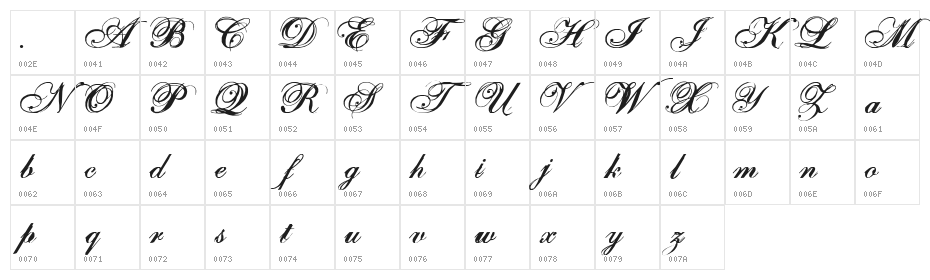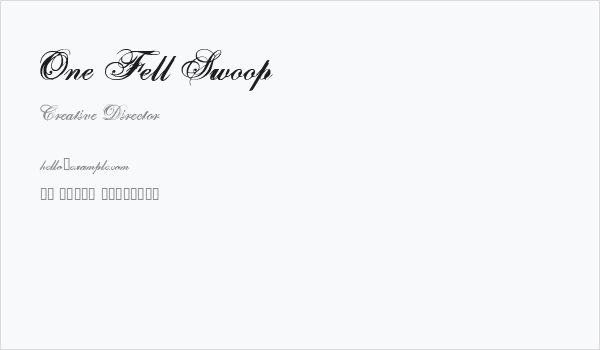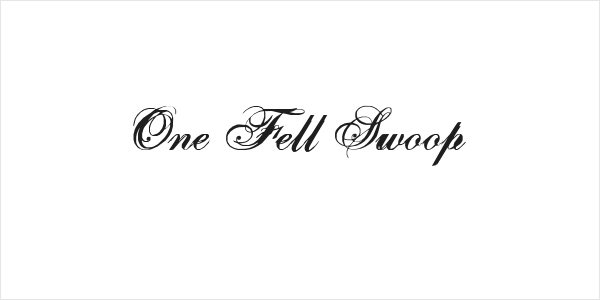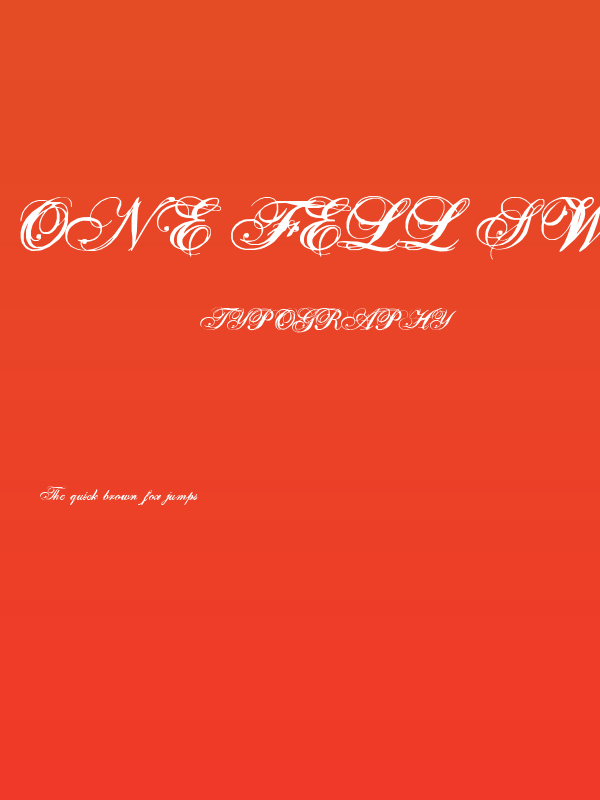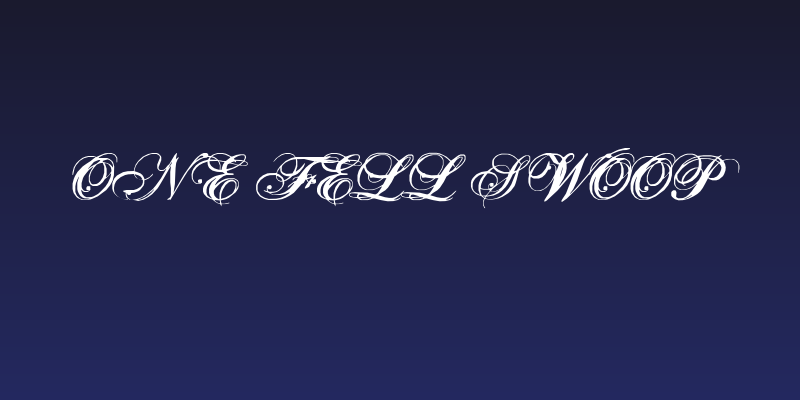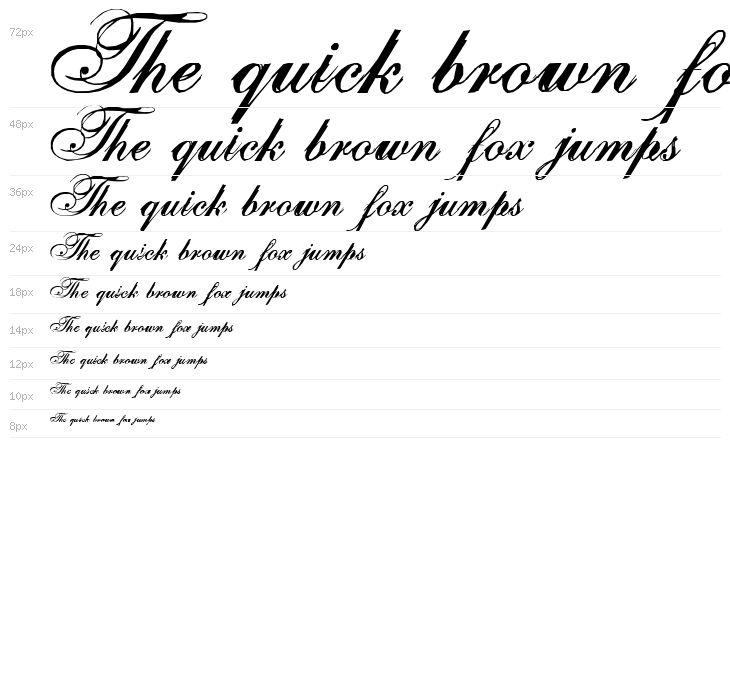
One Fell Swoop Font
✎ Calligraphic
| Kategorien | Calligraphic |
| Gesamtstil | Classic |
| Anwendungsfall | Logos, Headlines, Invitations |
| Vorgeschlagene Projekte | Ideal for wedding invitations, elegant branding, luxury product packaging, and decorative headlines. |